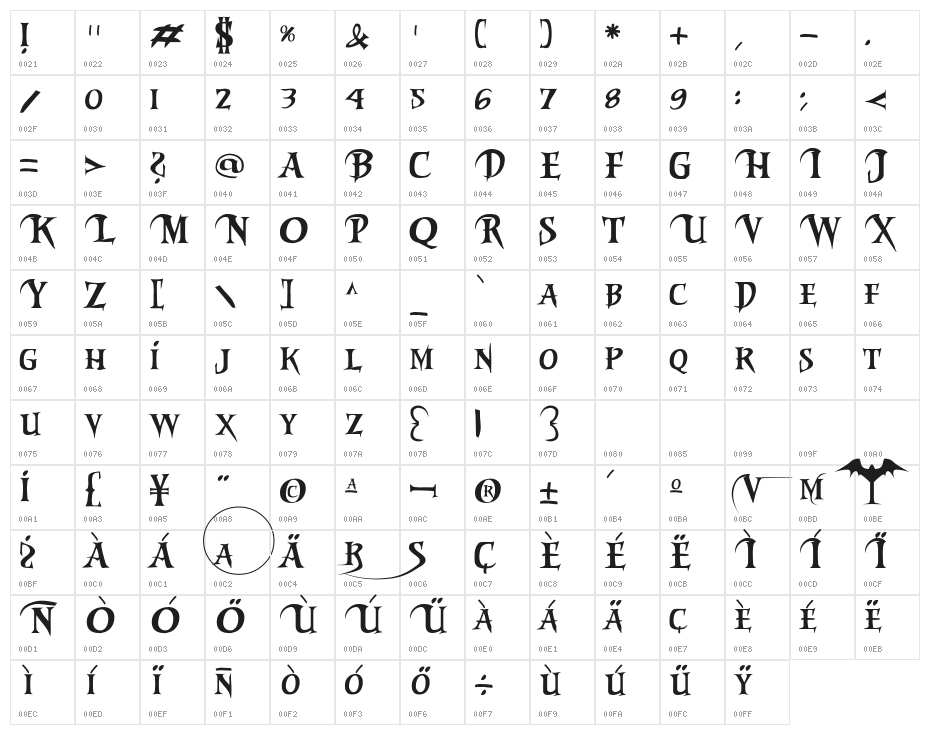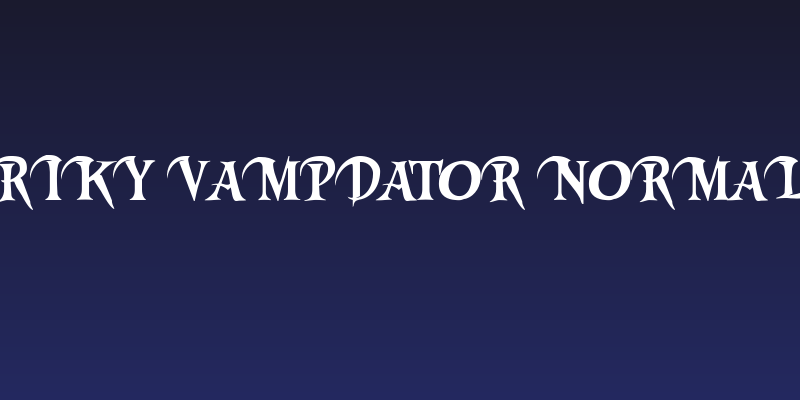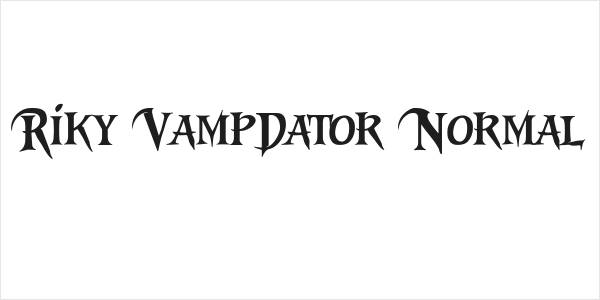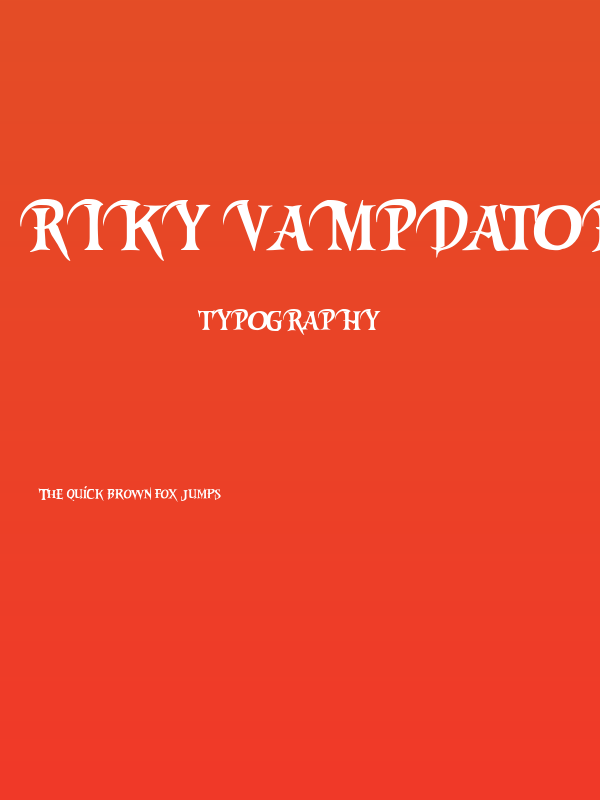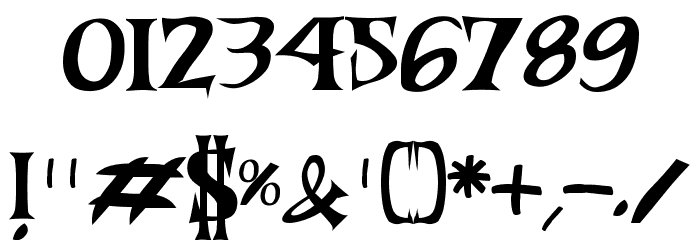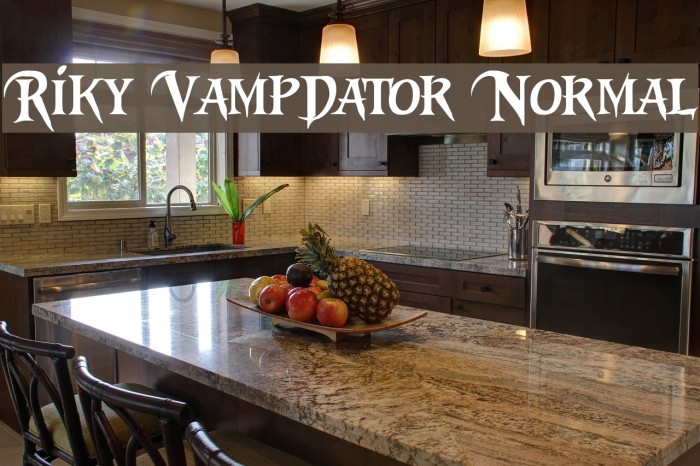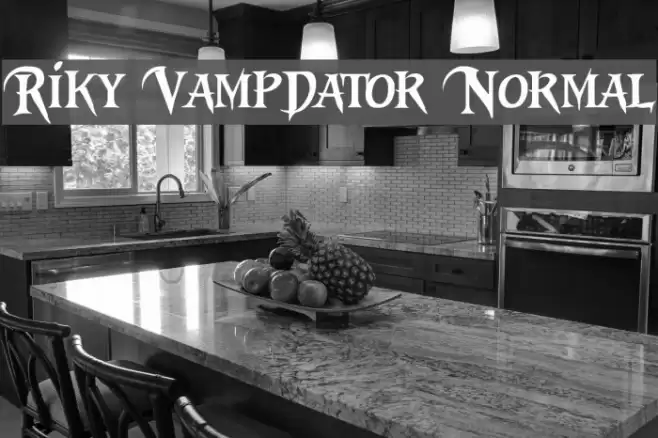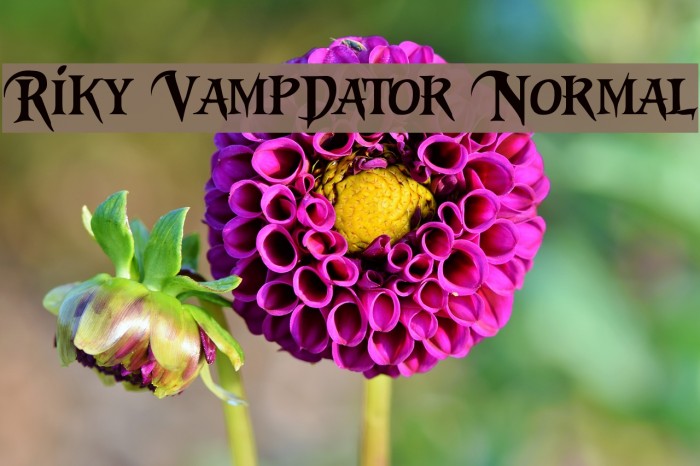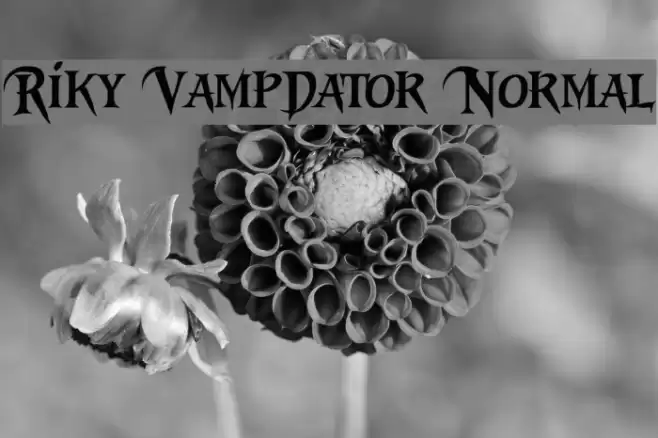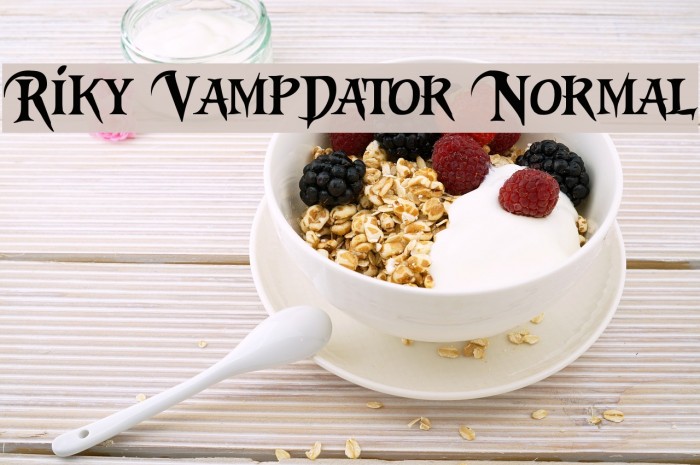
Riky Vampdator Normal Font
✎ Gothic
| 全体的なスタイル | Gothic, Dramatic |
| おすすめプロジェクト | Ideal for fantasy-themed designs, horror movie posters, video game titles, or any project requiring a dramatic, gothic touch. |